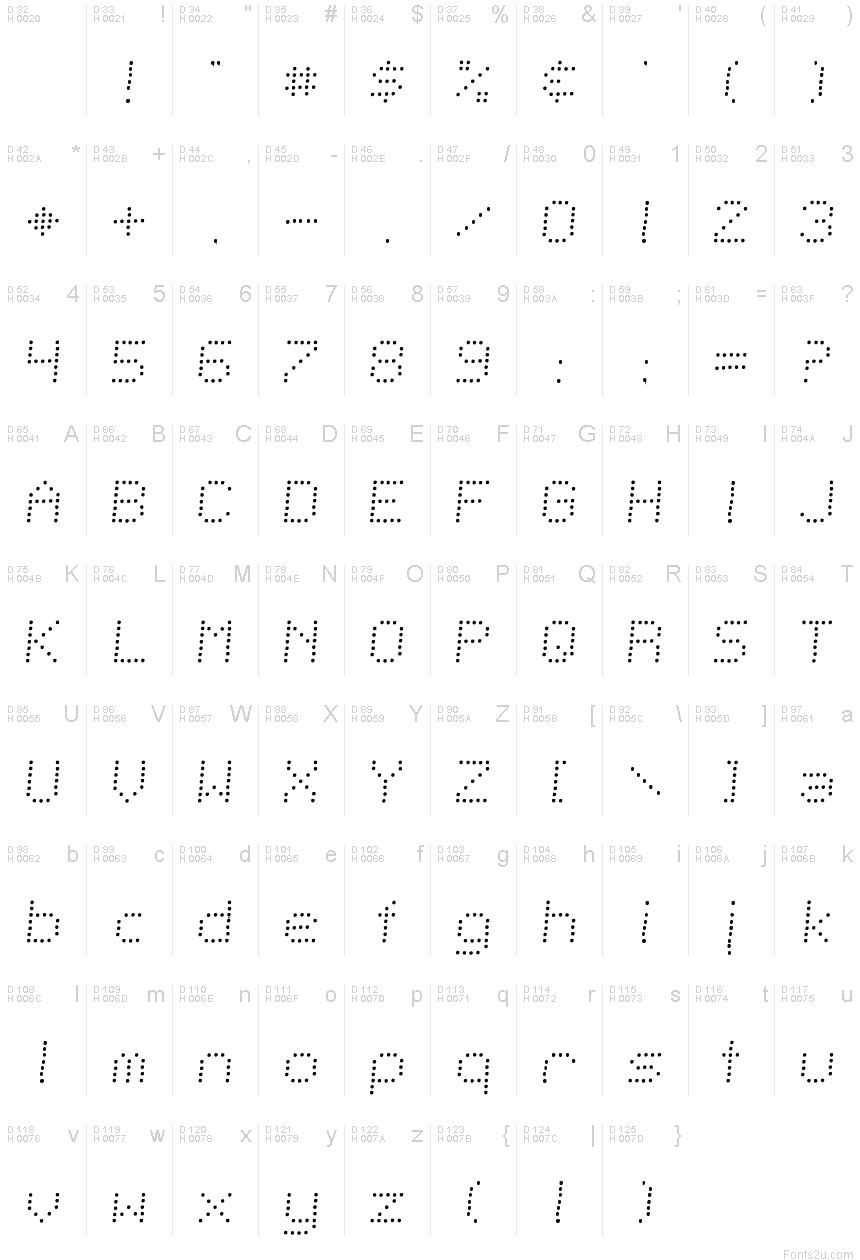
Telegraphic Light Italic od ShyWedge to darmowy cyfrowy krój typu display, nawiązujący klimatem do pagerów i tablic wyników z końca lat 90. Litery zbudowane są z równomiernie rozmieszczonych okrągłych punktów, dzięki czemu całość przypomina świetlne komunikaty zredukowane do samych sygnałów, a kursywa dodaje sztywnej siatce nieco dynamiki.
Krój naturalnie wpisuje się w techniczne plakaty, ulotki arcade, branding inspirowany interfejsami, ziny i plansze tytułowe – wszędzie tam, gdzie darmowy font ma nieść wyraźny elektroniczny klimat, nie stając się przy tym zbyt wygładzonym. Ze względu na wyraźnie modułową budowę, świetnie sprawdza się w krótkich nagłówkach, tekstach na okładkach i logotypach, które mają sprawiać wrażenie transmitowanych, a nie pisanych.